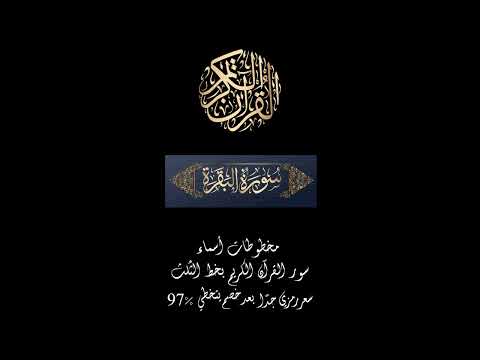
مخطوطات أسماء سور القرآن (114 سورة) بخط الثلث المجموعة الكاملة – ملفات فيكتور (Vector EPS) للمصاحف والقص بالليزر – Quran Surah Names
عدد مخطوطات المكتبة عدد 114 مخطوطة بخط الثلث
مخطوطات أسماء سور القرآن (114 سورة) بخط الثلث المجموعة الكاملة – ملفات فيكتور (Vector EPS) للمصاحف والقص بالليزر – Quran Surah Names
مخطوطات أسماء سور القرآن بخط الثلث The Names Of The Surahs Quran in Thuluth Font ،مكتبة مخطوطات من تنفيذ متجر مخطوطات ،احصل على هذه المجموعة الحصرية من مخطوطات أسماء سور القرآن المصممة بخط الثلث الفخم. المخطوطات متوفرة بصيغ مرنة (EPS, TTIF, PNG) لتضمن لك حرية استخدامها في جميع تصاميمك الرقمية والمطبوعة.
مخطوطات أسماء سور القرآن بخط الثلث وامتدادتها
مخطوطات أسماء سور القرآن بخط الثلث The Names Of The Surahs Quran in Thuluth Font هي مكتبة تحوي 114 مخطوطة بخط الثلث ،و تأتي متوفرة بالصيغ التالية (EPS, TTIF, PNG).
تعتبر حزمة مخطوطات أسماء سور القرآن المورد الرقمي الأهم والأكثر طلباً لكل دار نشر، مبرمج، أو مصمم إسلامي. بفضل الدقة المتناهية لملفات الفيكتور، يمكنك توظيف هذه المخطوطات الملكية بكل ثقة في مشاريع تصميم مصحف أو طباعة الأجزاء القرآنية، واستخدامها كعناوين رئيسية فاخرة عند تنسيق فهرس سور القرآن في الكتب والمؤلفات الدينية. كما أنها الخيار الأمثل والأسرع لمطوري البرمجيات عند تصميم واجهات تطبيقات قرآنية احترافية للهواتف الذكية.
المخطوطات المتضمنة في حزمة مخطوطات سور القرآن الكريم بخط الثلث:
1- مخطوطة سورة الفاتحة بخط الثلث